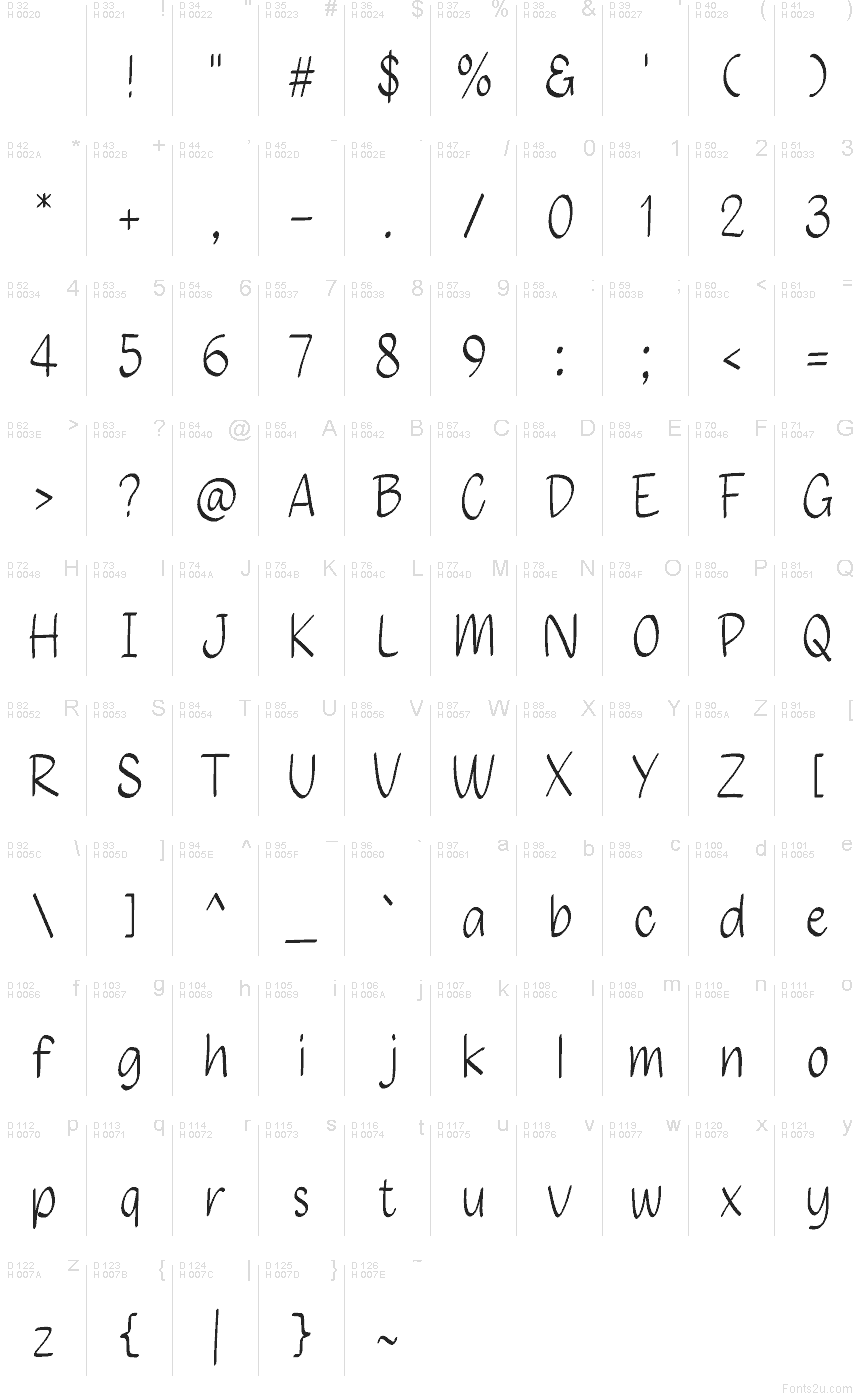
Content Cartoon
Content Cartoon від Hello Good Studio - це безкоштовний рукописний шрифт із високими, петлеподібними формами та вільним, невимушеним ритмом. Штрихи залишаються простими й відкритими, а заокруглені лінії та легка недбалість малюнка від руки надають йому живості, позбавляючи зайвої суворості.
Цей безкоштовний шрифт чудово підходить для графіки в соціальних мережах, брендингу, цитат, пакування та дитячих проєктів, оскільки його неформальний характер виглядає по-справжньому особисто, не стаючи при цьому неохайним. Content Cartoon також добре впишеться в заголовки блогів, запрошення, логотипи та легкі редакторські акценти, коли вам потрібно щось рукописне, дружнє та зрозуміле.